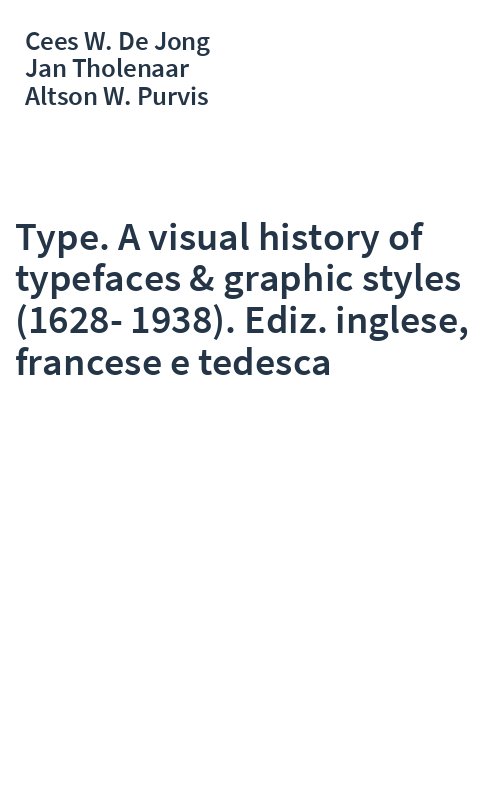
I due volumi di questo elegante cofanetto presentano i caratteri tipografici di una famosa collezione danese e ripercorrono la storia della stampa: il primo volume raccoglie caratteri anteriori al ventesimo secolo, corredati dal commento del curatore Cees de Jong e del collezionista Jan Tholenaar, il secondo è invece incentrato sul Novecento, con un excursus storico a cura di Altson W. Purvis.
Type. A visual history of typefaces & graphic styles (1628-1938). Ediz. inglese, francese e tedesca